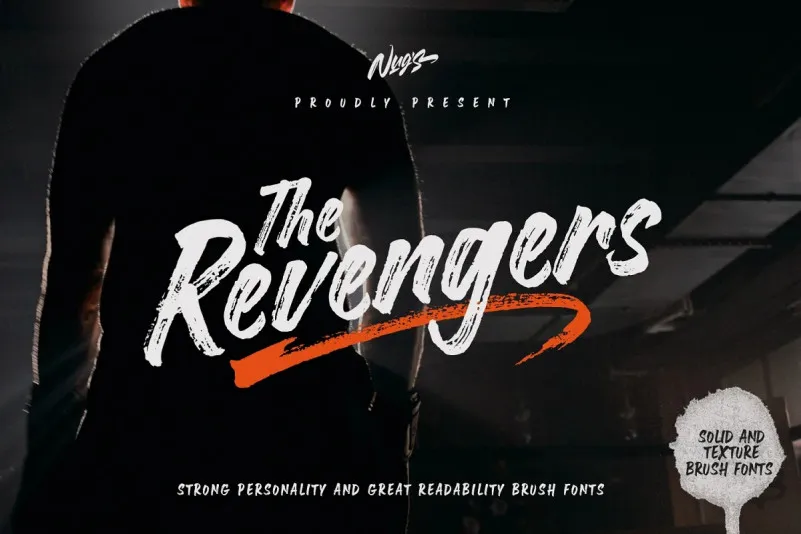
The Revengers Font – Download Grátis
A fonte The Revengers Font é uma elegante escolha para designers digitais atentos à sofisticação e aos detalhes. Criada pela NUGS, esta fonte segue um estilo de escrita a mão suave com traços fortes e pontilhados, ideal para criar logos impactantes ou design para cartazes. Com uma inclinação pronunciada e um tom resenhado, The Revengers Font é particularmente adequada para aplicar sobre fotos em postagens nas redes sociais, como um giroso de um texto estilizado a um fundo de imagem carregada com estilo. Além disso, ela se destaca perfeitamente nos designs de capas de livros e embalagens de produtos, proporcionando uma aparência sofisticada que complementará sua próxima peça visual criativa. Sua simplicidade não abala seu poder para moldar visuais memoráveis. Seja você um designer de logotipos ou alguém usando fontes em seus projetos online, The Revengers Font trará originalidade e elegância a qualquer projeto.